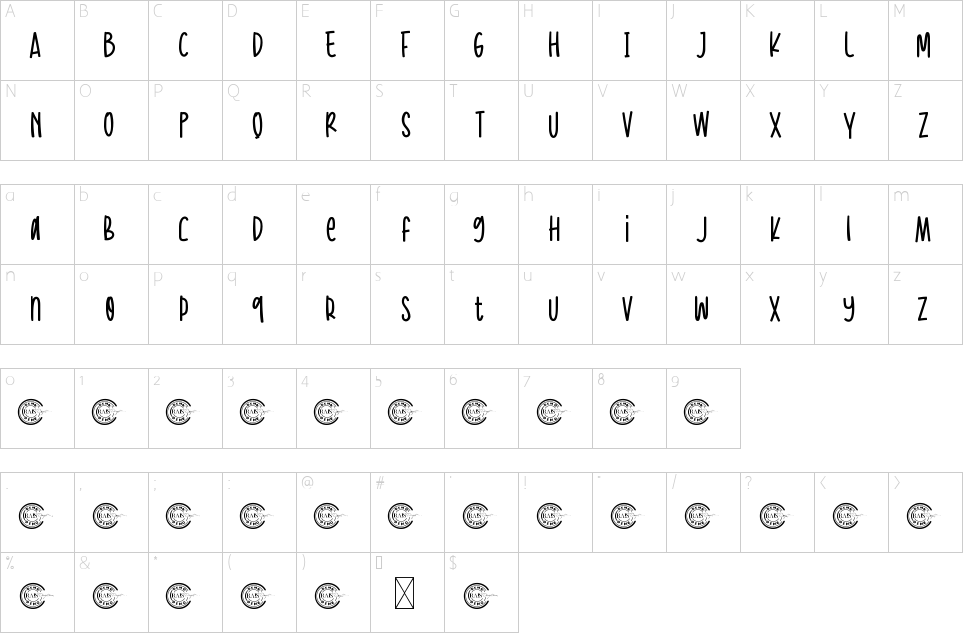
Aqui está uma descrição em português para a página de download da fonte Magic Burger: A Magic Burger é uma fonte original e divertida criada pelo designer desconhecido RaisProject. Esta fonte foi projetada para um público jovem, com grafismos e formas alegres que remetem a um querido fast-food, o hambúrguer. A Magic Burger traz uma estética divertida e descontraída, perfeita para adicionar um toque de estilo e personalidade a qualquer tipo de design. Esta fonte, disponível para download para Windows e Mac, foi instalada 241 vezes e está disponível para quem busca uma fonte gráfica para dar um toque especial ao seu design. Com Magic Burger, seu design ganhará um visual alegre e descontraído.